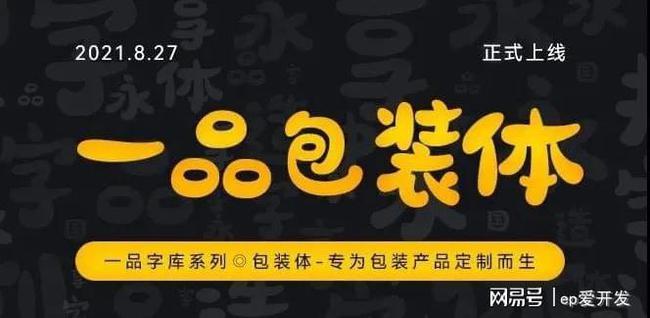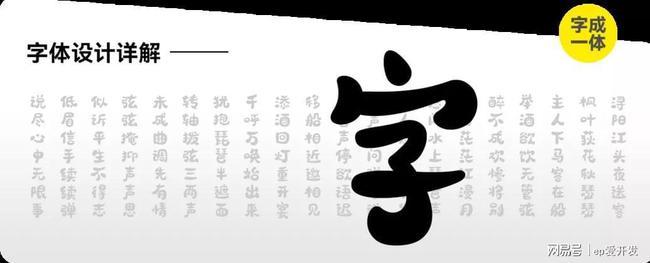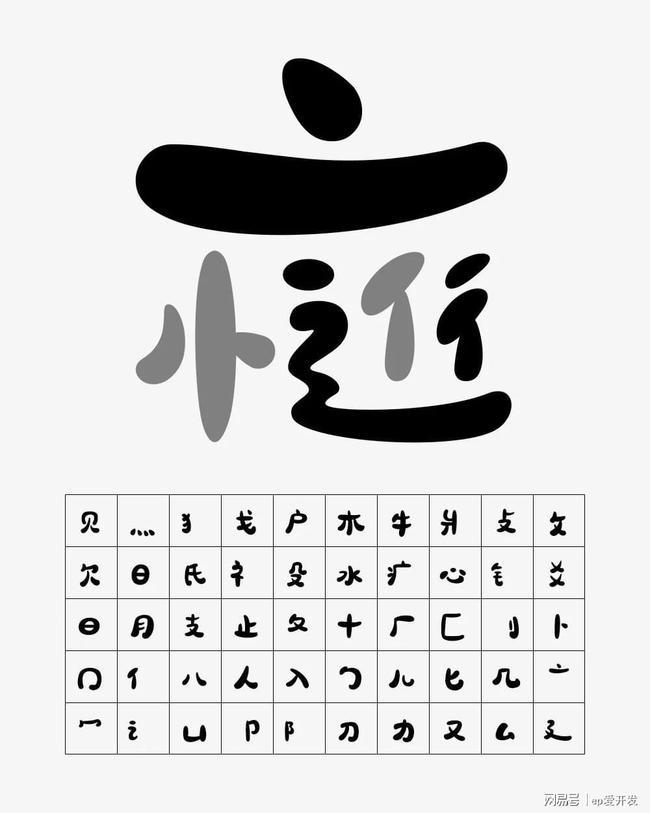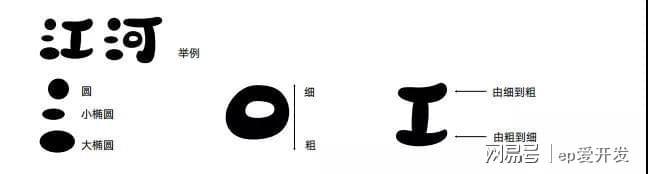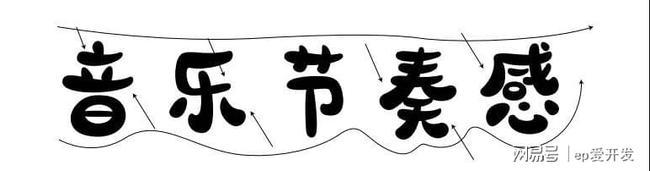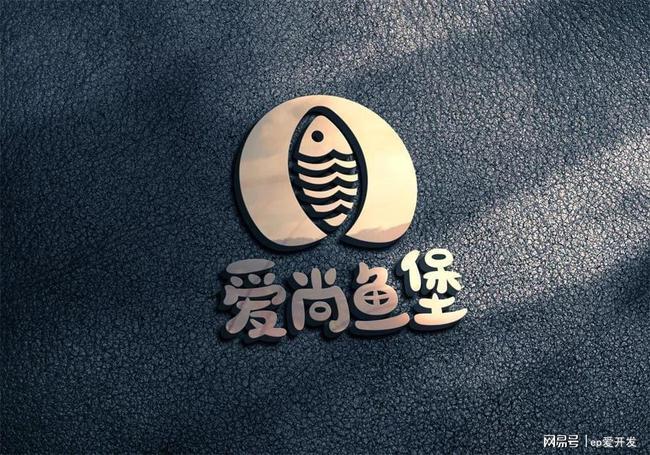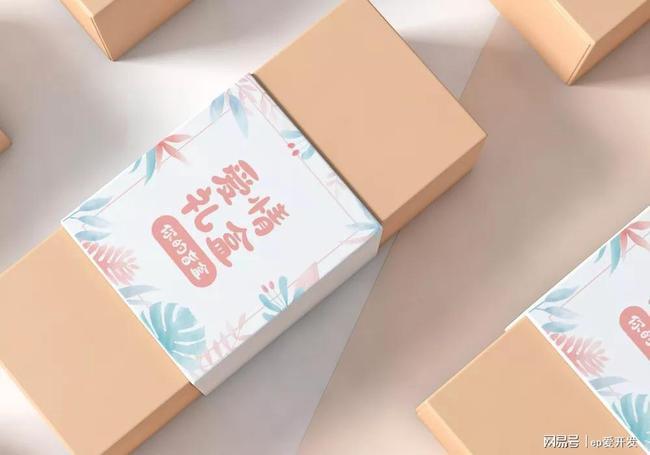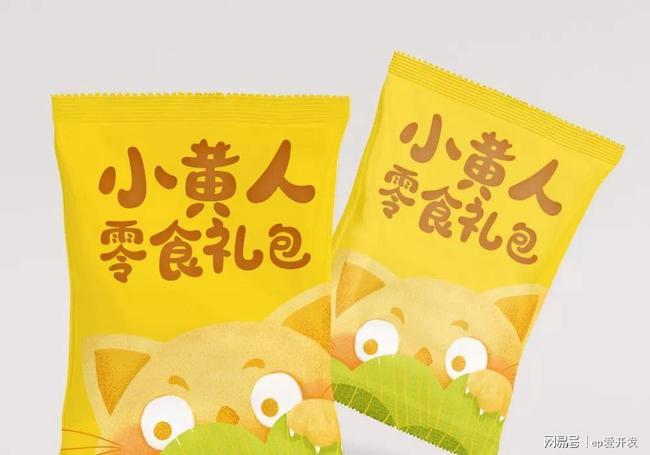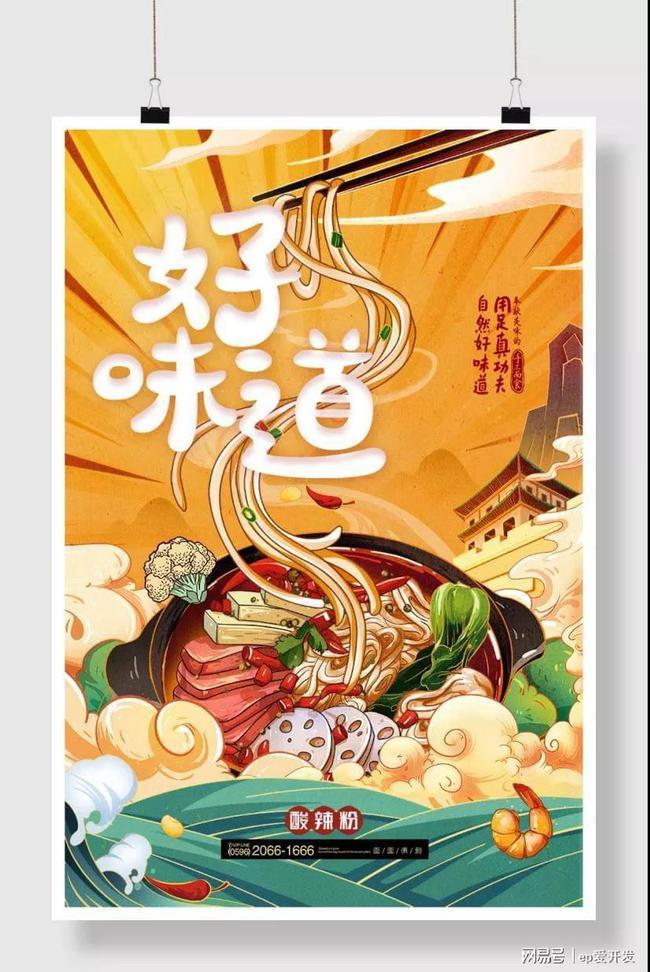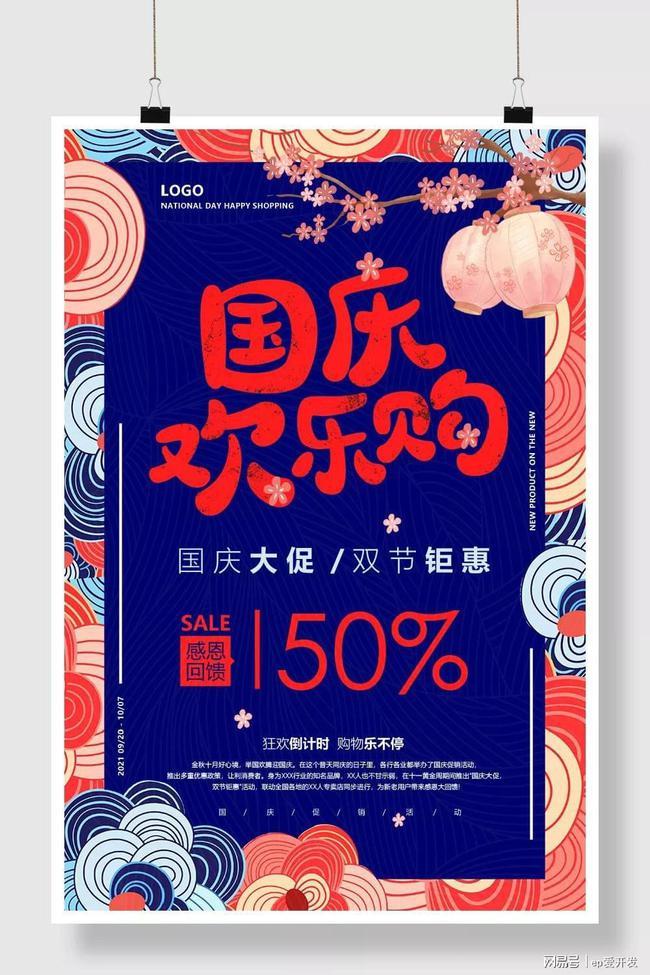
一品威客首款原创字体一品包装体正式亮相 酷贝街
近日,由一品威客推出的首款具有自主知识产权的原创字体——一品包装体正式上线了~
一品包装体专为包装产品定制而生,其轻松活泼、时尚帅气的设计风格,不免让人耳目一新。作为可盐可甜的“小包”字体,不仅有颜值更有内涵。具体而言,一品包装体有三大看点:
看点一:富有哲理的字体
一品包装体的创作灵感来源自有着悠久历史的行书。行书是介于楷书和草书之间的一种字体,大约出现在东汉末年,在宋代达到了新的高峰,与楷书的过于正经相比,行书给人的感觉是随性,潇洒灵动。
一品包装体通过将结合行书书法走势,取其部分精髓结合当代设计师手法创作而成。将中华传统文化与现代年轻人的喜好进行结合,行云如水,看似随意,却饱含深意,很契合当下社会需求和心态。
面对生活,你需要有“莫听穿林打叶声,何妨吟啸且徐行”的洒脱,和“行到水穷处,坐看云起时”的心态。
看点二:自带烟火气的字体
正所谓大道至简,至简至真,“人间有味是清欢”。
一品包装体,采用独特的笔画设计,通过每一笔每一画的细微变化,还原真实手写质感,摒弃传统工业化造字的横平竖直,精雕细琢,让设计带上生活气息。
圆润不均的手绘笔画,有人说那是带着傻傻的孩子气,有人说那是经受时光洗礼的纯真。返璞归真,难道不是另一种人生境界。
看点三:自带乐感的字体
正如自然万事万物都有它的美,一望无际的大草原让人心旷神怡,连绵的群峰让人心生敬畏,浩瀚的大海给人无尽遐想,每一款字体给用户带来的体验和感受也是不一样的。
一品包装体,以不拘的结构,错落不均的笔画,独自成群,站成队,排成行,串成有趣的音符,仿佛耳旁已经传来的那轻快、活泼、跳动的乐曲。
一品包装体为一品威客旗下酷贝街平台推出的首款具有自主知识产权的原创字体。字体以国标GB2312-80为基准,包含6763个简体中文汉字、数字和英文字母。
正如字体名字所阐述的,一品包装体首推运营场景为快消包装上,其次作为标题运用,当然并不限制多方位运用,包括海报、标志、横幅、桁架等。